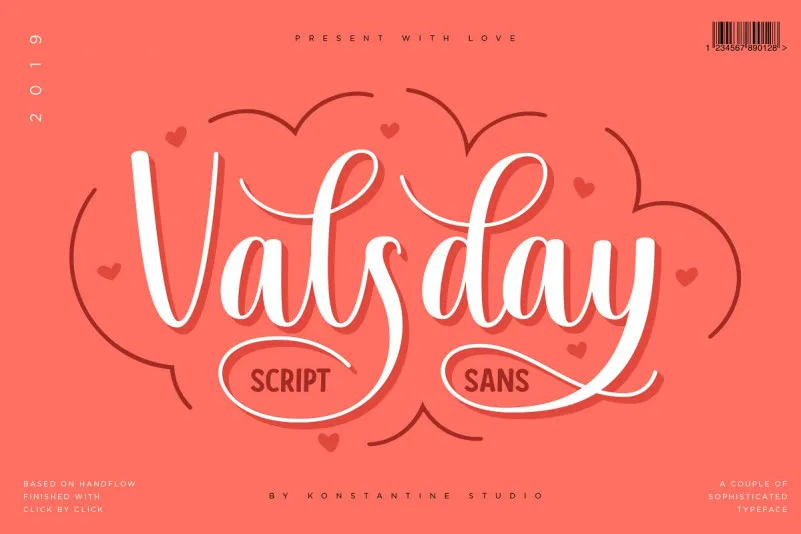
Valsday Script and Sans Font – Download Grátis
Esta é uma fonte script elaborada com delicadas tocas e curvas elegantes. Inclui também a versão serifada para aqueles que desejam mais detalhes ao aplicar a letra. Valsday Script and Sans é uma ótima opção se você está procurando por um tipo de texto leve e fluido, inspirado nos estilos modernos de escrituração e design de letras. Inspirada pelo amor cuidadosamente criado com mãos humanas, apresenta esta fonte script clara e suave. A versão sans serif bold complementa perfeitamente a combinação para criar um casal perfeito. Você conhece os melhores casais que não podem viver sem o outro? Essa combinação de fontes é exatamente como isso.